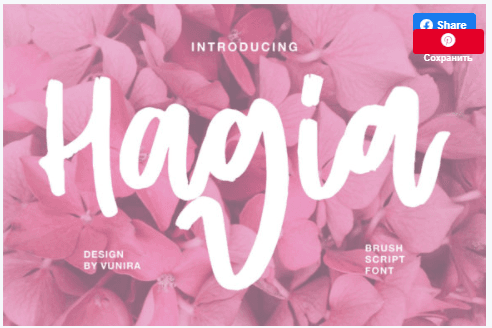
Hagia Font
Hagia - это стильный рукописный шрифт с краской и уникальными буквами. Этот шрифт был специально разработан для тех, кому нужен красивый и освежающий вид своего дизайна.